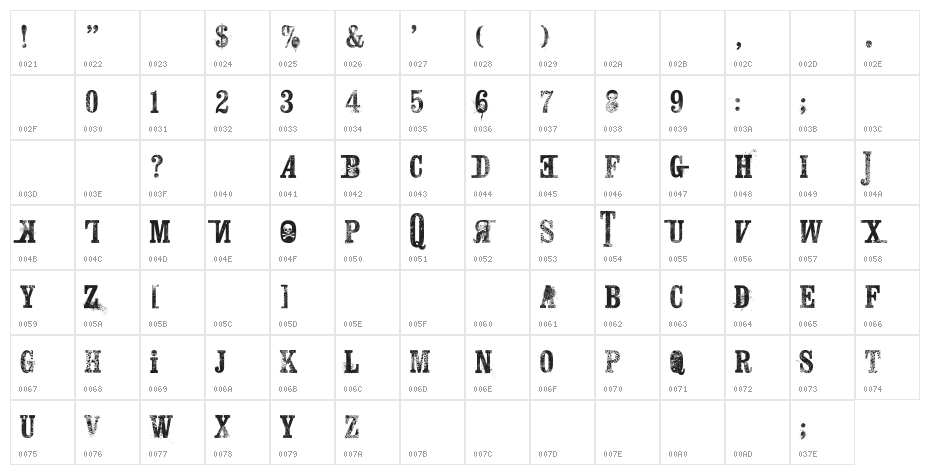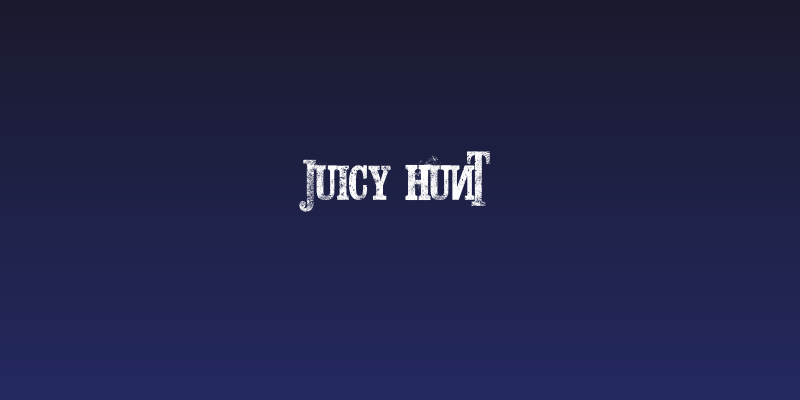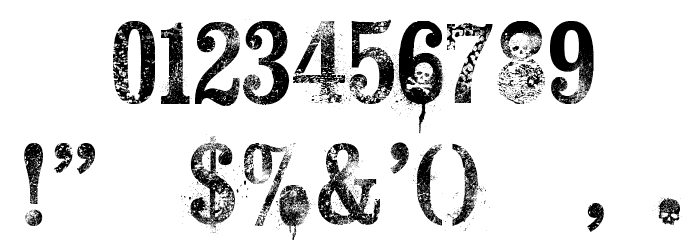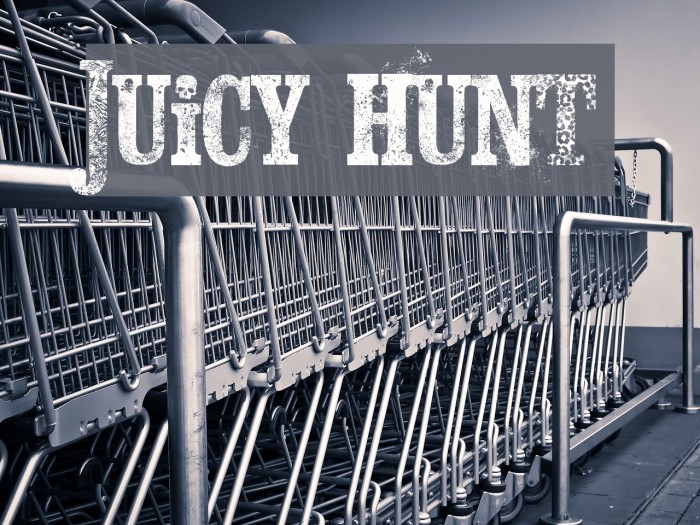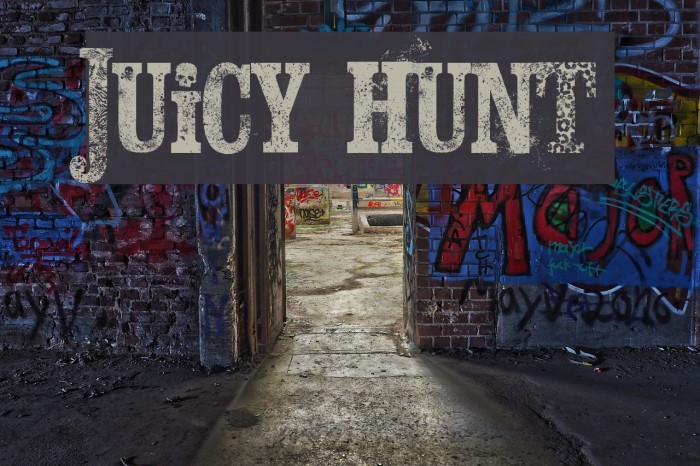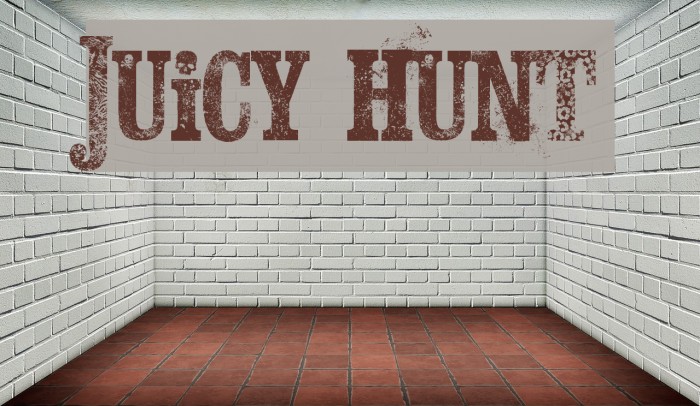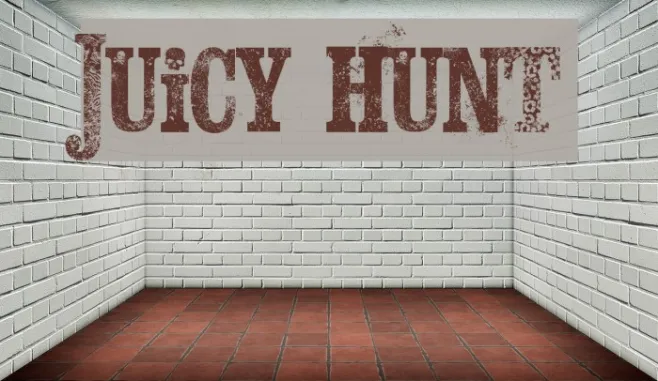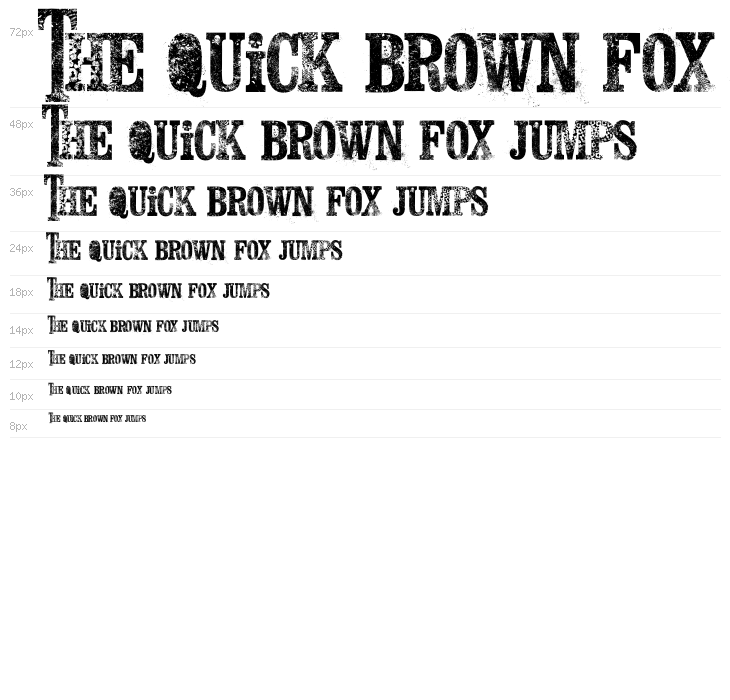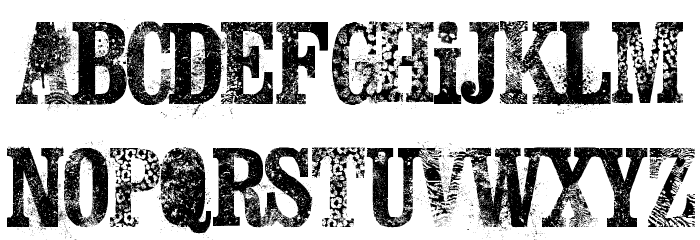
Juicy Hunt Font
| Projets proposés | Perfect for album covers, posters, branding for edgy products, or any design needing a vintage or rebellious touch. |